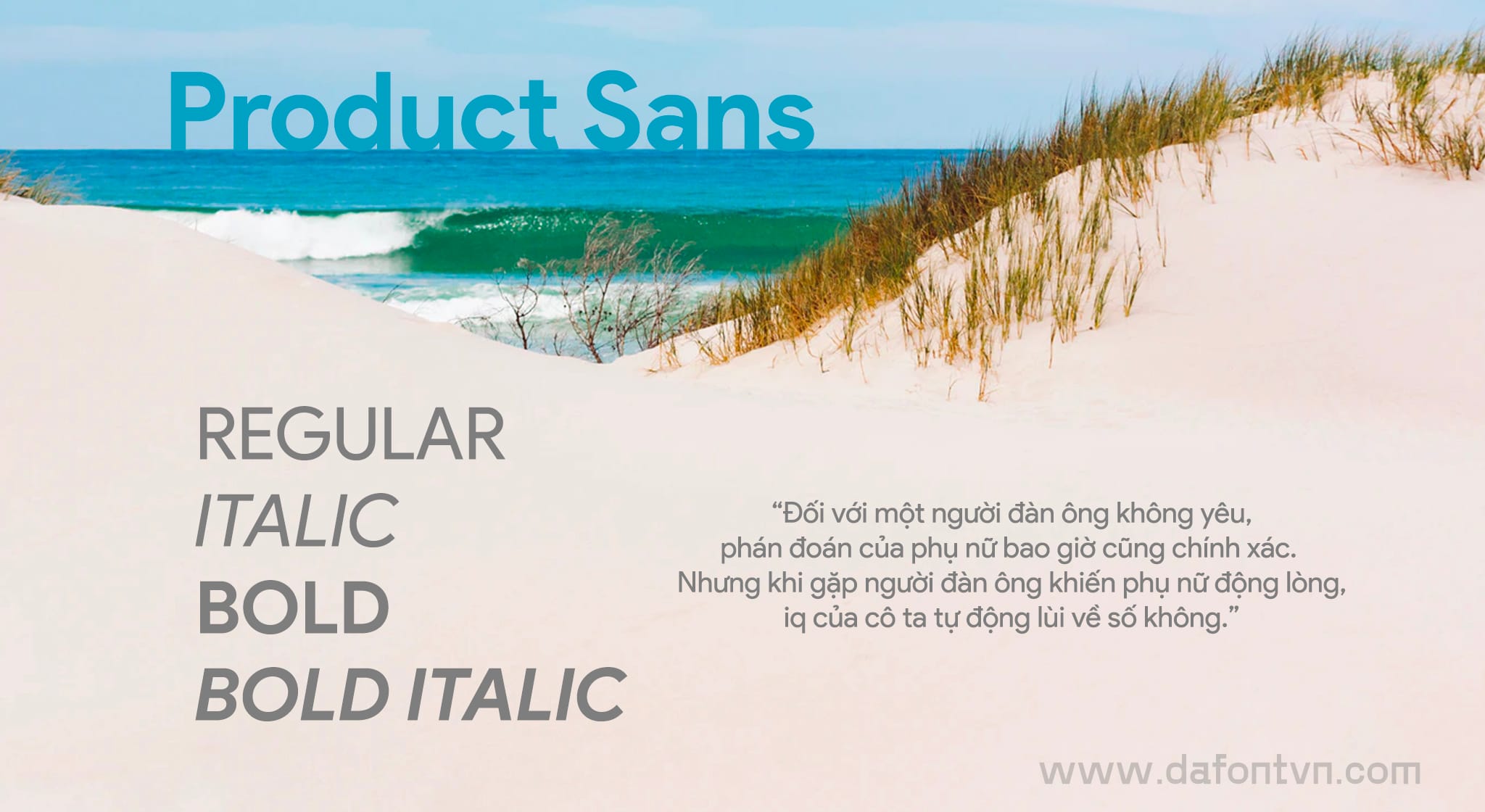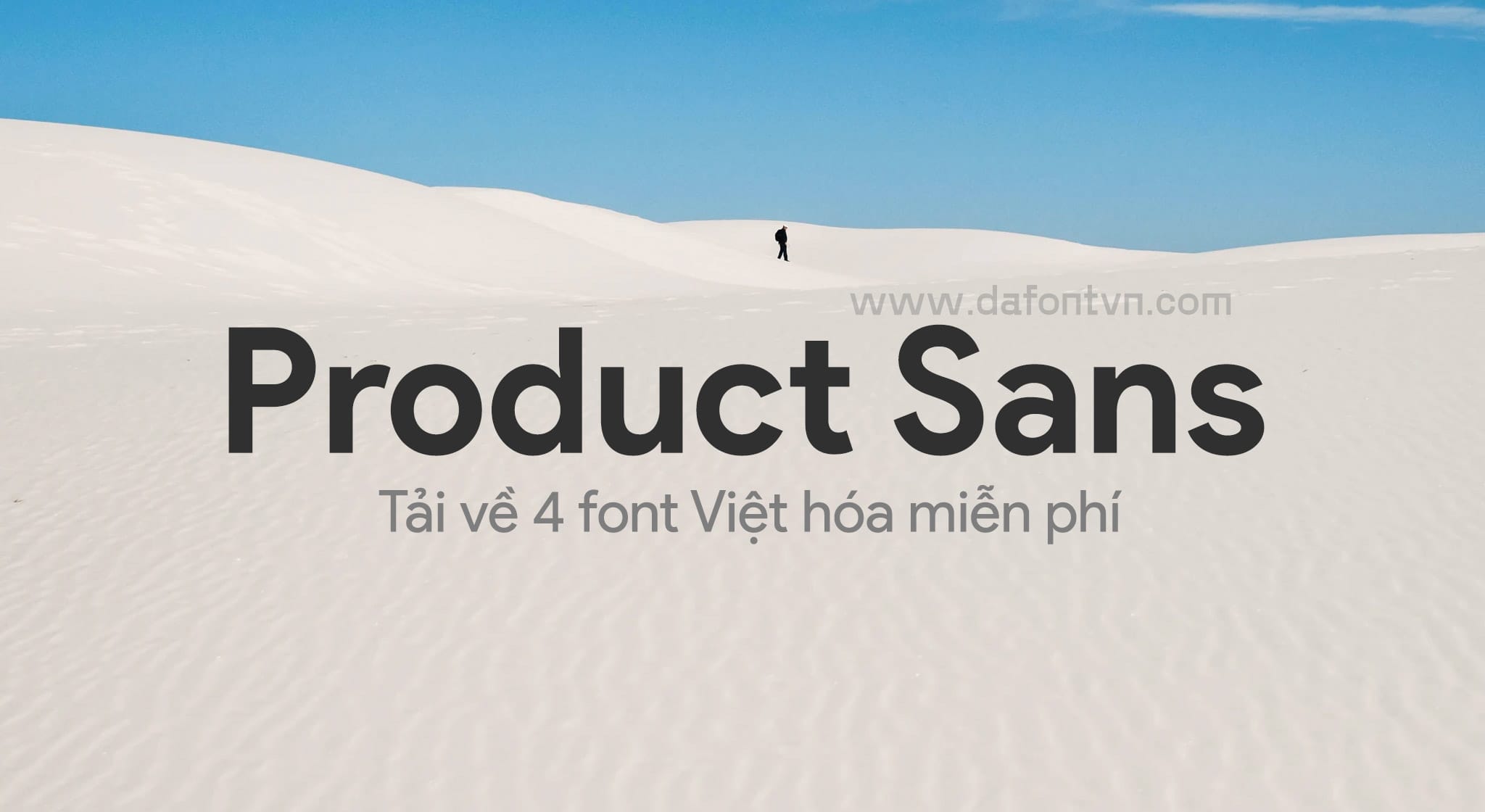
Product Sans là một kiểu chữ sans-serif hình học do Google tạo ra cho mục đích xây dựng thương hiệu. Nó thay thế logo cũ của Google vào ngày 1/9/2015. Khi thương hiệu của Google ngày càng phổ biến hơn trên nhiều loại thiết bị, Google đã tìm cách điều chỉnh thiết kế của mình để logo của nó có thể được mô tả trong không gian hạn chế và vẫn nhất quán cho người dùng trên các nền tảng đơn giản, khiêm tốn và dễ gần.